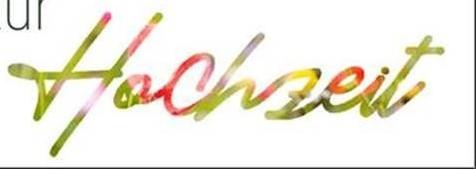
Welche Schrift ist das auf der Einladungskarte?
ich bin auf der Suche nach der Schriftart, in der das Wort "Hochzeit" auf dieser Einladungskarte geschrieben wurde (siehe Foto). Möchte dazu gerne weitere Drucksachen erstellen.
Ich weiß es leider nicht … aber da mir die gezeigte etwas unausgegoren vorkommt: bestünde eventuell die Möglichkeit einer Alternative ?
Nur als Beispiel: